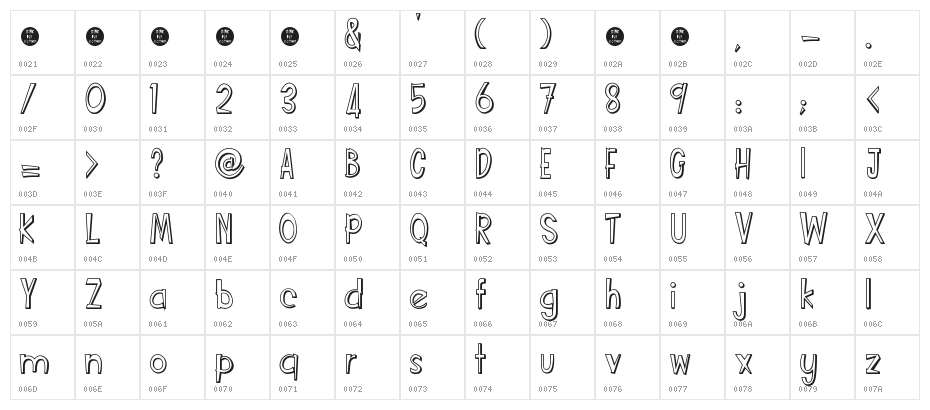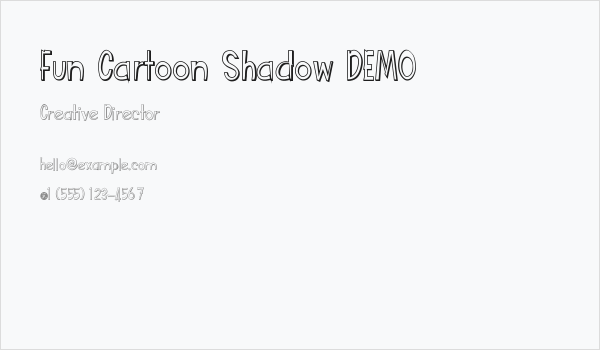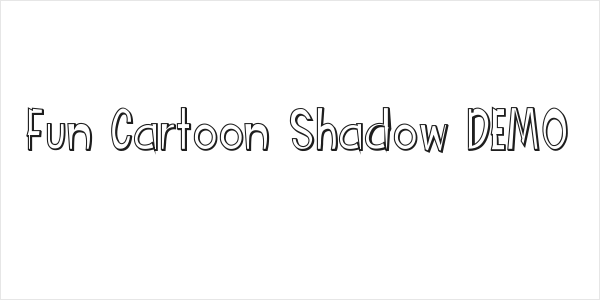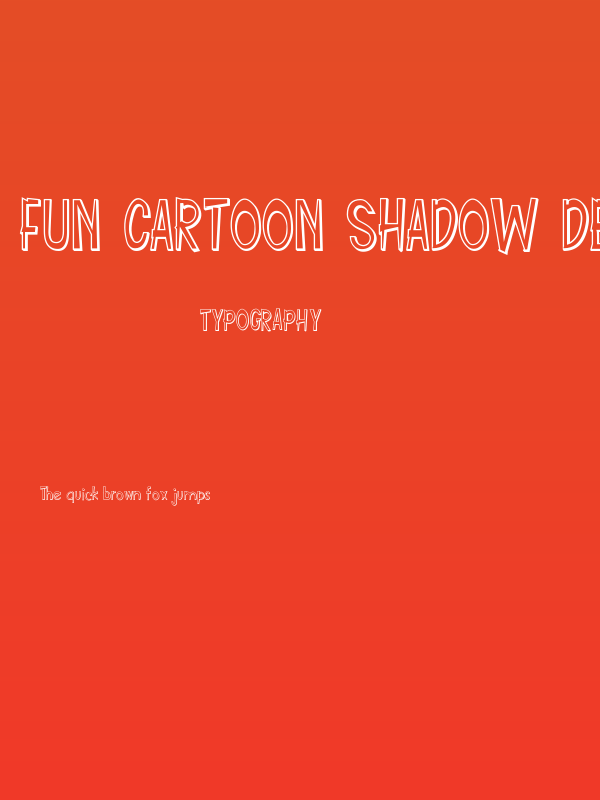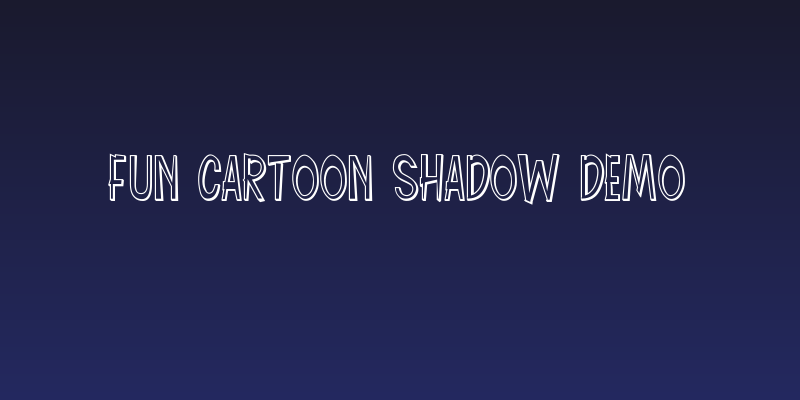
Fun Cartoon Shadow DEMO Font
| Gesamtstil | Fun, Playful, Cartoon |
| Anwendungsfall | Headlines, Posters, Branding |
| Vorgeschlagene Projekte | Ideal for children's books, comic strips, playful branding, and eye-catching posters. |